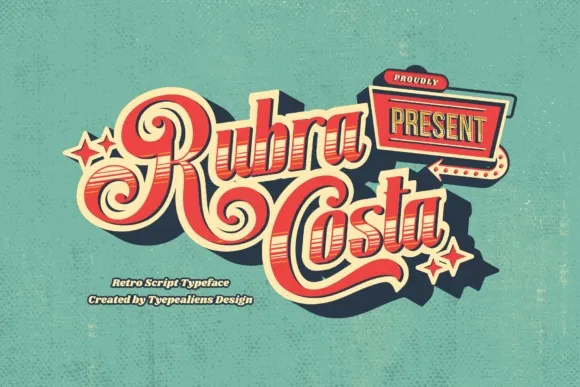
A Rubra Costa Font é uma tipografia script que oferece aos designers uma opção versátil para projetos visuais modernos e clássicos. Desenvolvida pela ilhamtaro na plataforma de 99designs, essa fonte apresenta um estilo robusto e elegante, com alternativas estilísticas no formato OpenType. Suas linhas grossas e seu charme vintage garantem uma personalidade única que se destaca em logos, embalagens, propagandas nas redes sociais e muito mais. Com suas alternativas estilizadas nos caracteres maiúsculos, a Rubra Costa Font proporciona um toque de ornamento perfeito para títulos ou cabeçalhos. Seu design é ideal tanto para quem busca uma presença sólida em sua identidade visual quanto para os criativos que desejam introduzir um toque vintage e moderno em seus trabalhos visuais, seja ele para a criação de logotipos, embalagens ou conteúdo publicitário. Seja você designer de gráficos ou marca, este script pode ser uma escolha inteligente para seu próximo projeto visual.